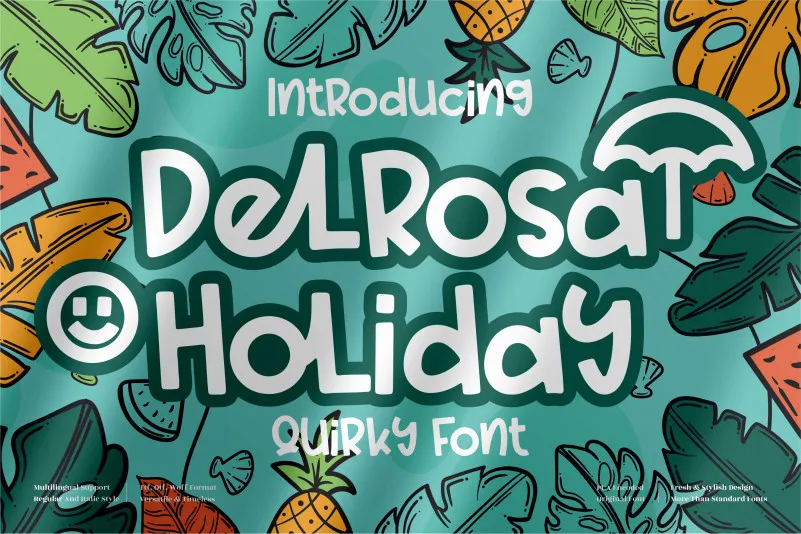
Delrosa Holiday Font – Fonte Grátis
Delrosa Holiday Font
A fonte “Delrosa Holiday Font” é uma escolha perfeita para atividades criativas envolventes que buscam unir estilo com alegria e autenticidade. Inspirada no uso das cores vivas e na linguagem descontraída, essa fonte traz consigo um ar de brincadeira natural que se destaca nas mídias digitais atuais. Perfeita para aplicações infantis como cartazes escolares, posters de festivais ou mesmo para designs corporativos mais divertidos e modernos, a “Delrosa Holiday Font” é uma opção ideal para quem busca um toque especial que fique a salvo no meio da grande variedade. E o melhor? Ela foi criada por perspectype, conhecido pelo seu trabalho de alta qualidade em fontes display, tornando-a ainda mais valiosa e versátil para qualquer tipo de projeto visual.